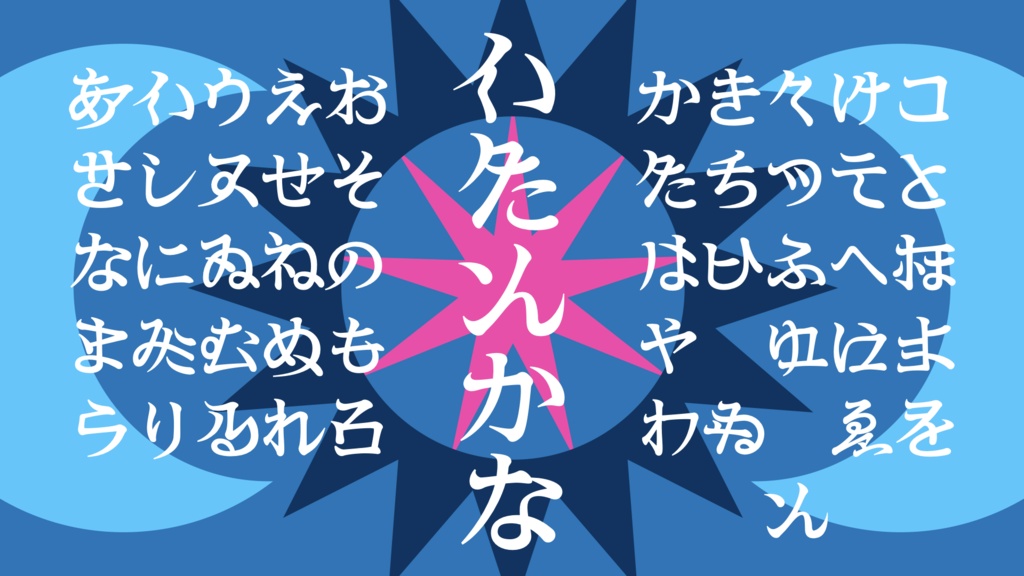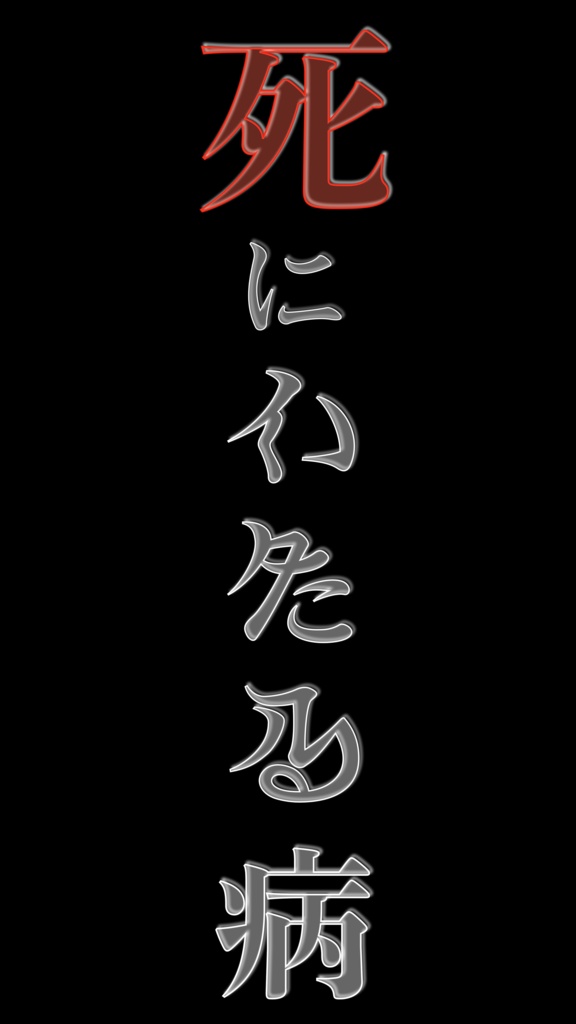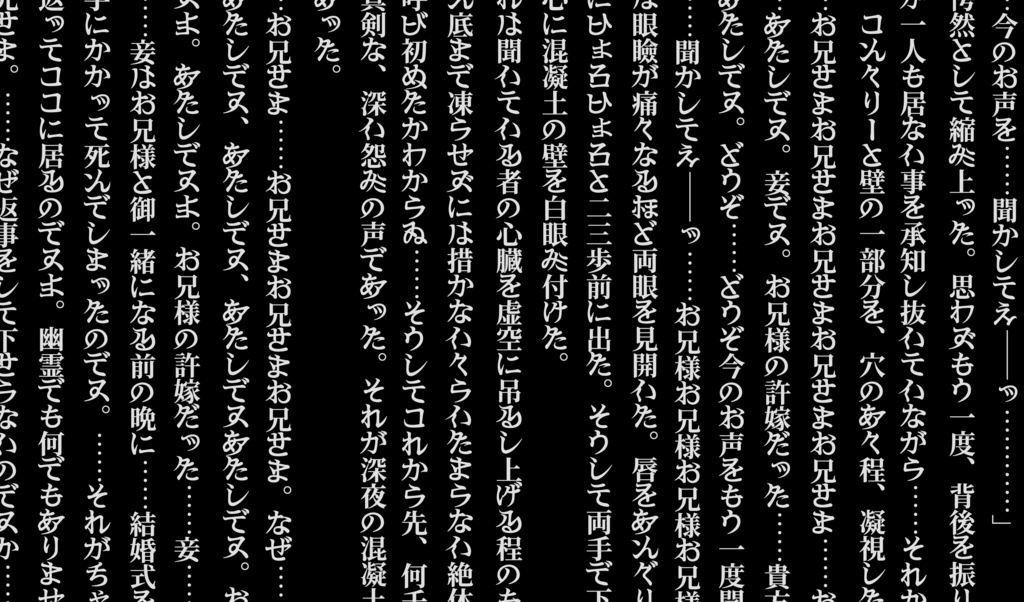
異端仮名『怪』- 異界の仮名文字フリーフォント
2019年に公開した「異端仮名」の新書体『怪』です。通常版の異端仮名に比べて読みやすく、怪しげになっています。 2019年バージョンはこちらからダウンロード可能です。 https://fontring.booth.pm/items/1395946 【ライセンス】 SIL Open Font License 1.1です。このライセンス下ではフォントの印刷利用、商用利用、派生フォントの配布、Webフォントとしての利用などを自由に行っていただけます。 【こんなシーンで使えます】 ・異端仮名はひらがなとカタカナが融合した書体なので、簡単に読めます。可読性を損なうことなく、並行世界の文字や異質な存在のセリフを表現することができます。 【仕様】 ・ひらがな、カタカナに同一の字形を当てています。 ・縦書きに対応しています。 ・『怪』では、無印の異端仮名(https://fontring.booth.pm/items/1395946)とは字形が異なる文字があります。 ・ウェイトはBoldのみです。 作ったフォントが使われているのを見るのが好きです。作品を投稿する際にタグ「#異端仮名」をつけたりクレジットに記載したりしていただくと見つけやすいので嬉しいです😉 このフォントを紹介される際、Boothのサンプル画像は自由にご利用ください。 【投げ銭版について】 投げ銭版は無料版と全く同一です。お気をつけください。 投げ銭の代わりとして、下記のフォントの購入もご検討いただければ幸いです。大変励みになります。 ・欧文/カタカナフォント CORORIN https://fontring.booth.pm/items/871969 ・欧文フォント Lemonin https://fontring.booth.pm/items/1156944 【告知など】 フォントのバージョンアップのお知らせはPixiv Fanboxで投稿します。フォローお願いします🙏 https://www.pixiv.net/fanbox/creator/31276656